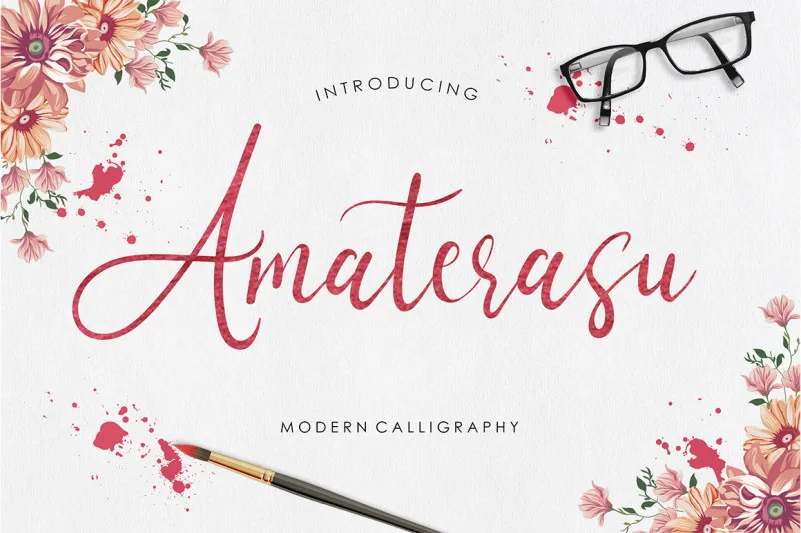
Amaterasu Calligraphy Font – Download Grátis
Amaterasu Calligraphy Font é uma fonte de script para chamados que traz beleza única à sua próxima criação. Dedicada aos entusiastas do design gráfico e das letras artesanais, esta fonte incorpora movimentos elegantes que são ideais para dar um toque atraente às suas mensagens. É perfeitamente adequada para o seu trabalho de design, seja para cartões de aniversário, materiais de marca ou até mesmo uma criação única e personalizada da sua identidade visual. Seja o logotipo do seu negócio, as páginas de blogue, a embalagem dos seus produtos ou até mesmo um editorial de revista, esta fonte oferece flexibilidade para alcançar diferentes objetivos visuais. Ideal para quem quer dar um toque especial aos seus designs, Amaterasu Calligraphy Font é especialmente adaptada para cartões de casamento e permite-lhe explorar suas capacidades criativas de forma única. Essa fonte é uma excelente escolha para quem deseja trazer um ar elegante e sofisticado ao seu trabalho visual. É perfeita para aqueles que buscam algo além da monotonia dos outros tipos de fontes e estão sempre em busca de novas maneiras de expressar sua arte.